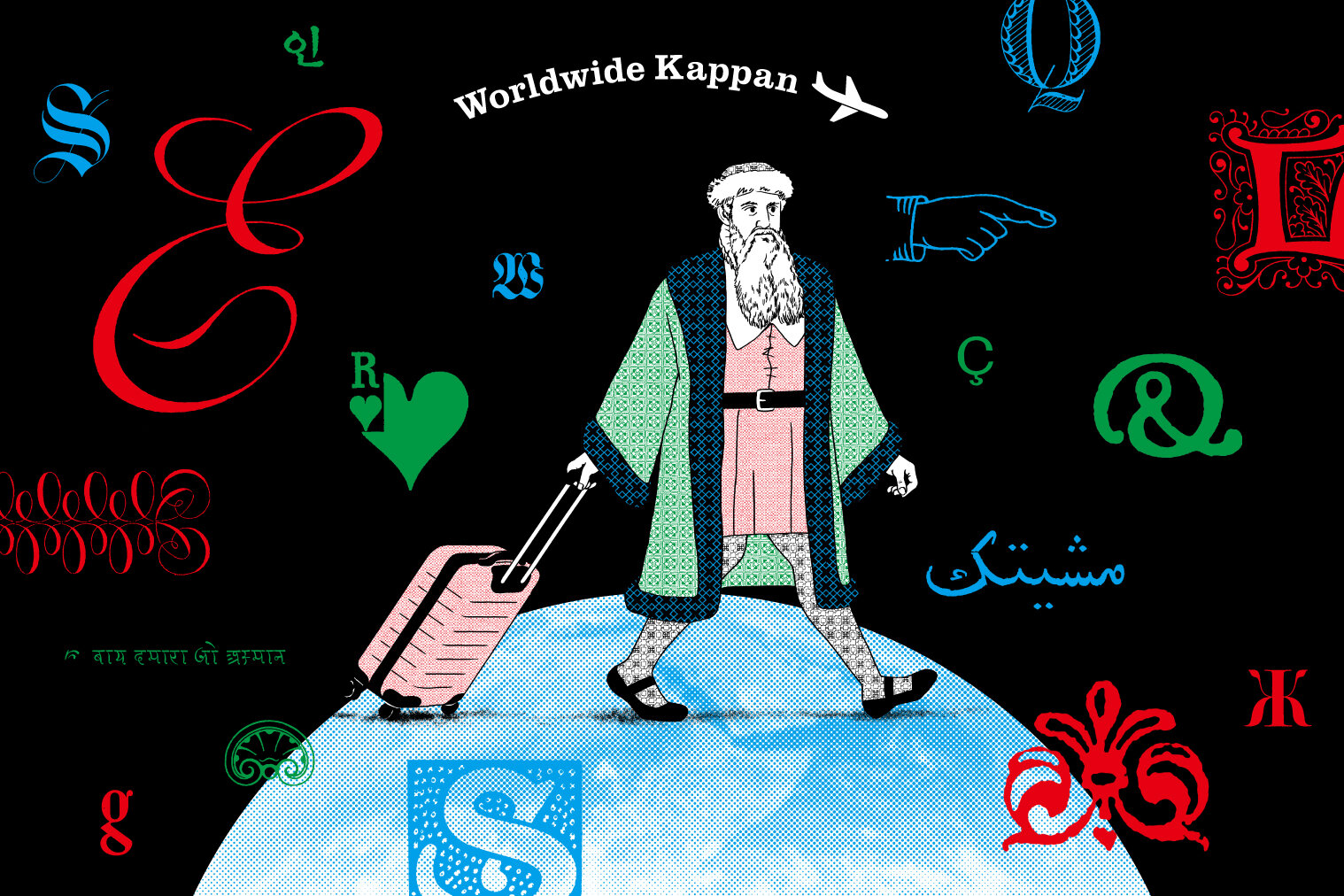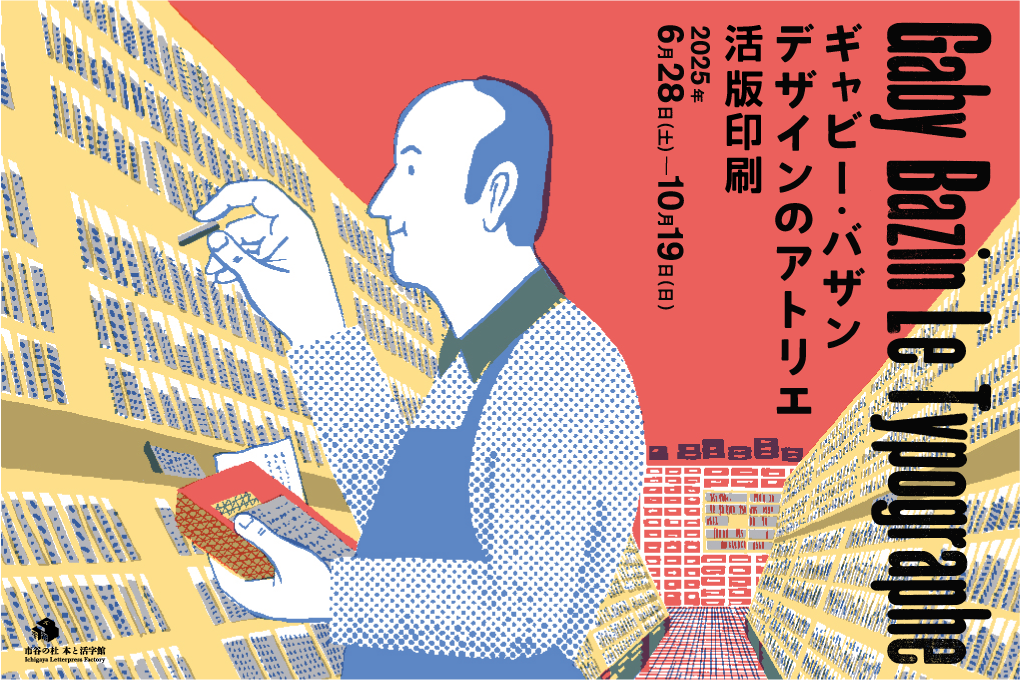
身の周りにある本や雑誌がどのような背景でつくられているか、そのノウハウはどのような場面に応用されているか、など、さまざまな切り口で本づくりのプロセスや技術を紹介します。
みんなでつなぐ 100年目の本づくり
ワールドワイド活版印刷 Worldwide Kappan
活版印刷をめぐる、世界一周の旅に出ましょう。本展では、世界各地で活版印刷を支える人びと──活字を作り続ける鋳造所、1文字ずつ活字を並べて印刷し、書籍を制作する印刷所、それらの技術と知識を次代へ伝える文化施設──を紹介します。
明朝体
水やコメにたとえられることもある明朝体。現在私たちが日常的に目にするデジタルフォントから、「明朝体の二大潮流」とされる築地体・秀英体の誕生まで、150年以上にわたる明朝体の歩みを時代をさかのぼりながら紹介します。
あつまれキラキラ★百箔繚乱
その輝きで人々を魅了する「箔」。どんな風にできているのか、どんな風に加工されているのか、身近だけど意外と知らない箔について詳しくなれる展覧会。
展示室にはメタリック・ホログラム・顔料箔が100種類以上!多種多様なキラキラをご紹介します。